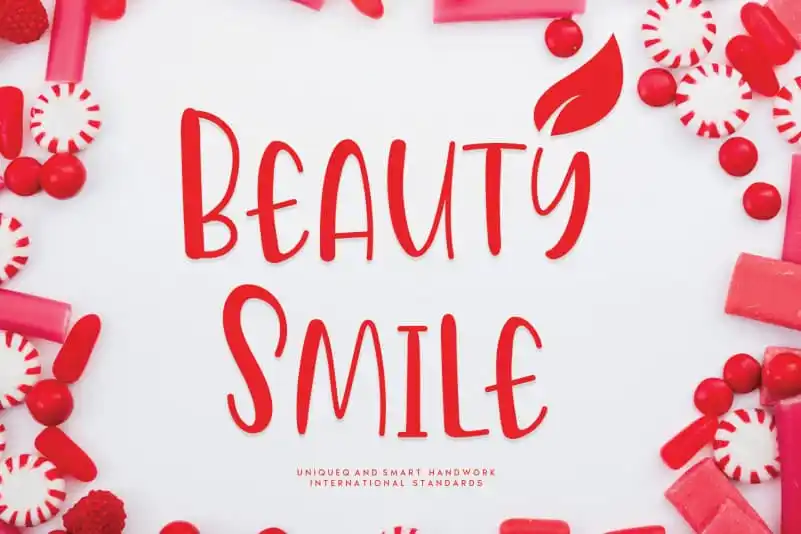
Beauty Smile Display Font – Download Grátis
Descubra a beleza do design com Beauty Smile Display Font. Desenvolvida pelo designer andikastudio, essa fonte especial é perfeita para quem busca uma experiência única e criativa em seus projetos digitais. Beautifulemente handwritten, ela oferece um toque único que vai além da simples utilização de qualquer outra fonte existente. Perfeito para adicionar um charme extra a aplicações digitais como banners, flyers ou até mesmo design de sites pessoais. Experimente e venha se surpreender com sua elegância e versatilidade. Você não quer perder essa oportunidade de deixar seu trabalho de design ainda mais profissional.